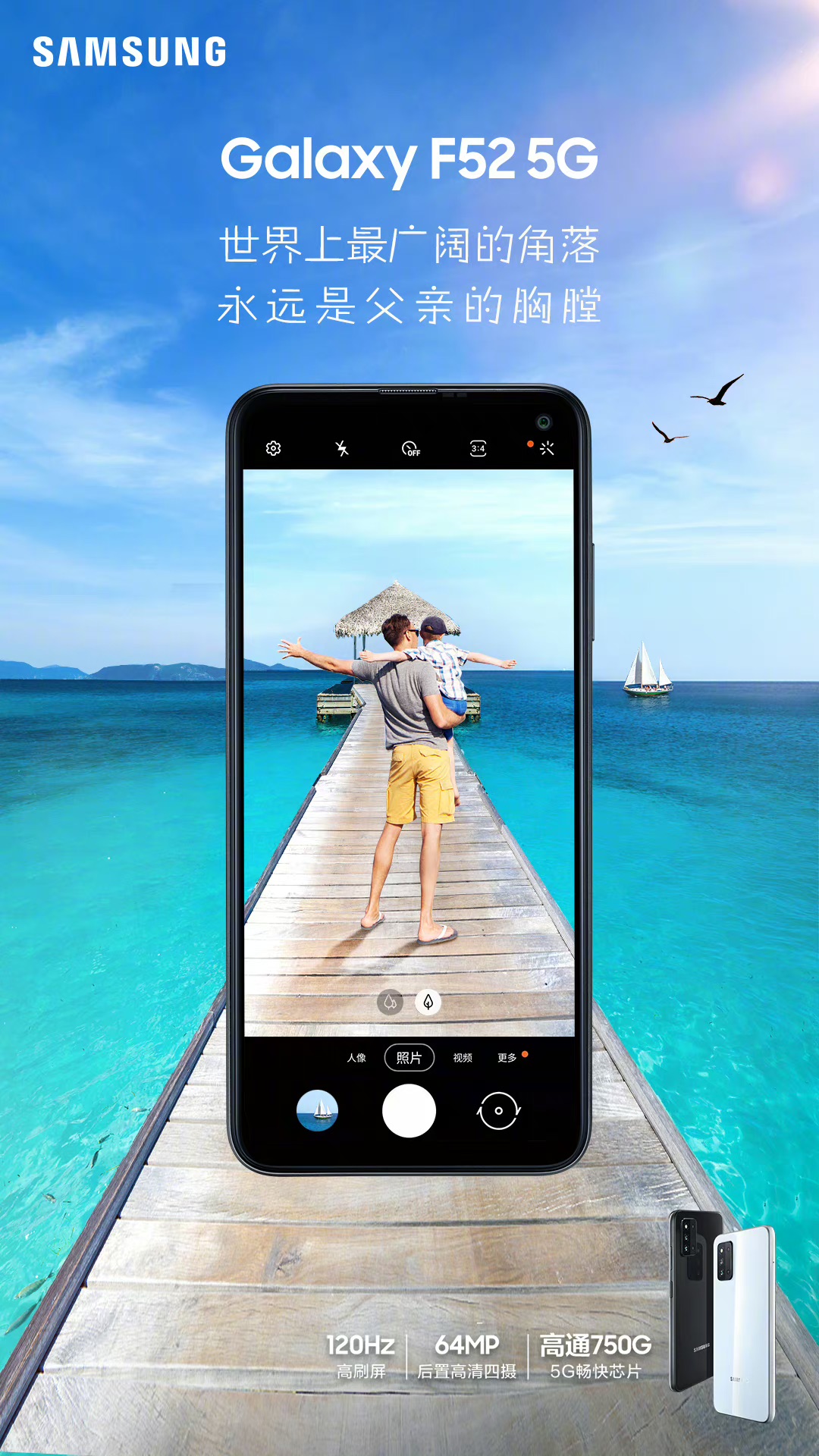
方正稚艺
齐立
黑体、创意字体
2000
方正稚艺是一款富有孩童气息的创意字体。这款字体的笔形主要是由圆点和直线构成,重心偏低,有儿童书写的简拙;笔画交接处多有书写意味的分离,笔画中圆形的点画与其他直线笔画形成对比,灵动可爱。字形轮廓整体统一,具有一定的易读性。方正稚艺的个性乖巧灵活,清新萌动。不但适用于儿童类的书刊、品牌广告和产品包装设计,以及社交网络的个性化用字,还可胜任简短的正文排版。